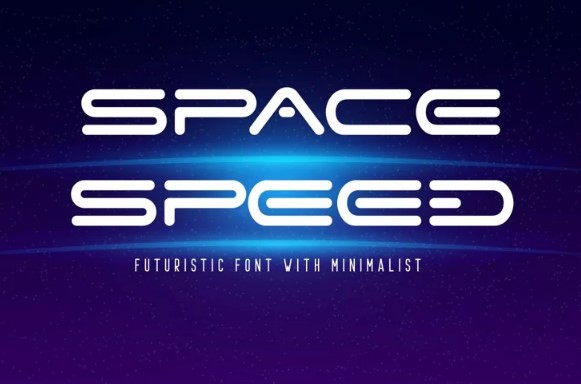
[Fontbundles] Space Speed Font (2021)
Space Speed Font
- футуристический шрифт с минималистичными, широкими буквами. Шрифт с футуристическим краем, геометрическими углами, идеально подходит для технологической темы. Он включает английские прописные буквы, основные знаки препинания и цифры. Рекомендуется использовать его с большими интервалами между буквами, но вы можете отлично настроить его для собственного дизайна, использовать его для создания логотипов, эмблем, постеров.